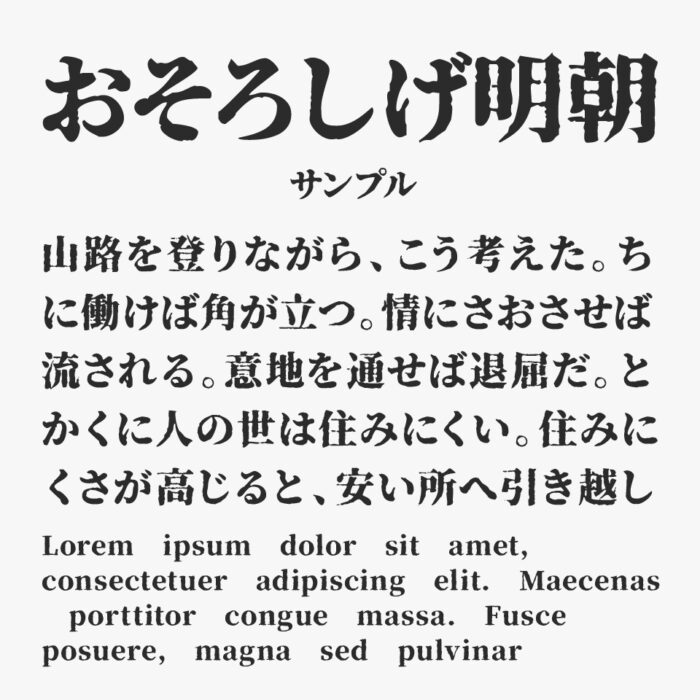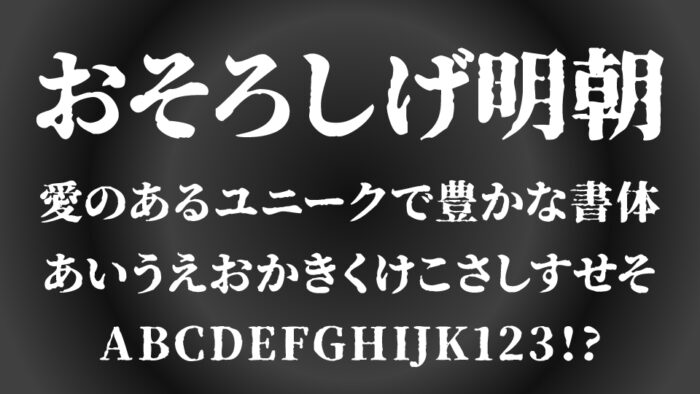
おそろしげ明朝フォントは、Noto Serifをベースとして、擦れと揺らぎが生む不穏な空気感が印象的な、ホラーテイストの明朝体です。
太めなウェイトの力強さに加え、墨がにじんだような輪郭や抑揚のあるストロークが、独特の恐怖感を感じさせるフォントとなっています。
恐怖や不安、廃墟的な静かな恐怖を感じさせるようなフォントです。